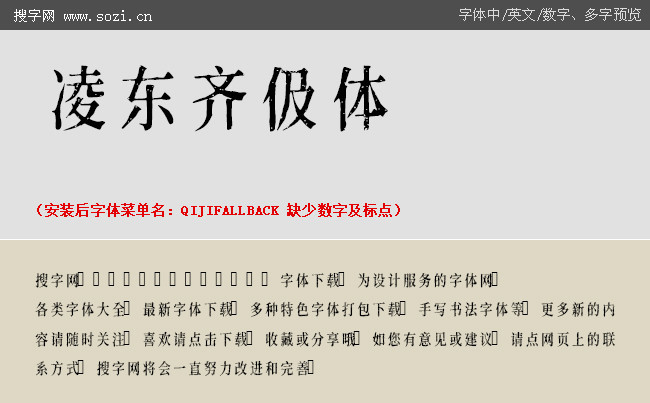
凌東齊伋體
搜字網(wǎng)給大家提供一款凌東齊伋體中文字體下載,凌東齊伋體摘自明代木版印刷書籍《凌閔刻本》,采用半自動計算機(jī)視覺和OCR制作而成的一款字體。所以缺少英文、數(shù)字及標(biāo)點。其筆畫風(fēng)格書法特征濃郁,比常規(guī)的明朝體更具韻律感,富有人文氣息。而且可以免費商用!適合海報設(shè)計、包裝設(shè)計等宣傳廣告等應(yīng)用。